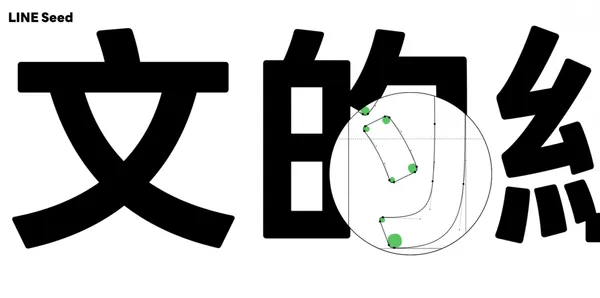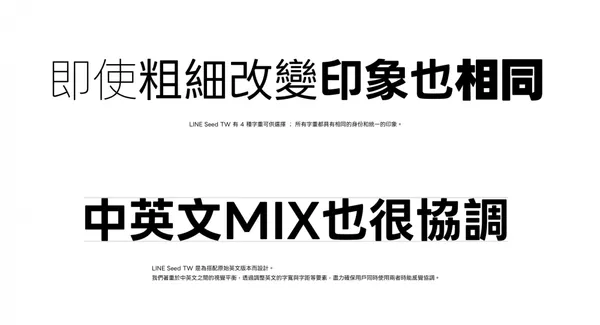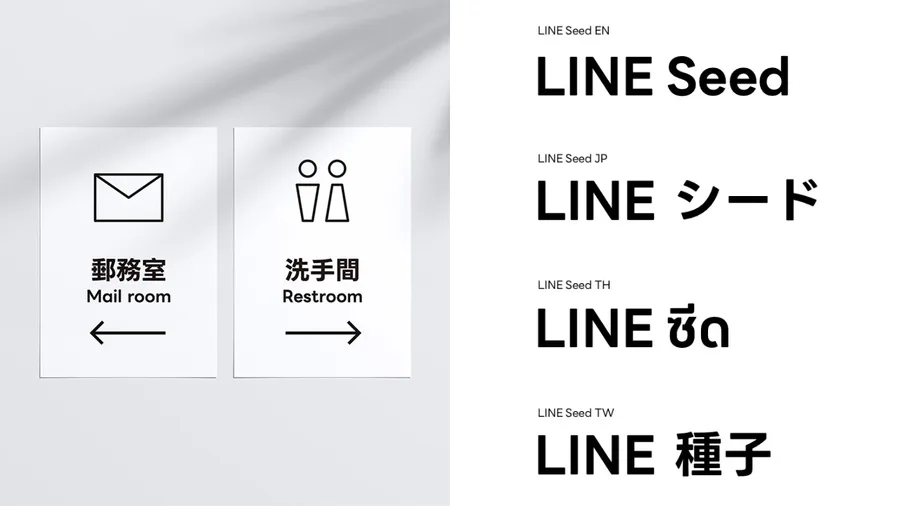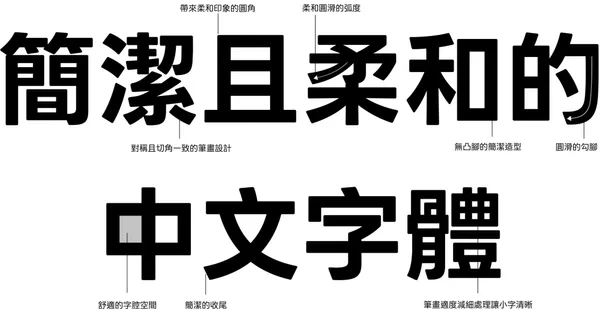
3 年磨出 14,038 字!LINE Seed 繁中版 4 款粗細一次收,可免費下載「商用也 0 元」
歷時近 3 年設計,LINE 首款自有字體「LINE Seed」,正式推出繁體中文版,共提供 4 種不同粗細的字重,可於 LINE Seed 官網免費下載,個人與商業用途均可使用。
LINE Seed 是一款強調簡約設計的無襯線字體,適用於數位、平面等各式使用場景。它保留了 LINE 品牌 Logo 的幾何造型,同時融入柔和的曲線,兼具理性與親和度。即使在中、英文字體並置時,視覺上也能和諧呈現。
攜手華康字型,LINE Seed 繁中字體設計亮點
LINE Seed 是由 LINE 所開發的企業字型,隨著品牌在全球提供服務,該字型也先後釋出了日文、英文、韓文、泰文等語言版本,如今,LINE 與華康字型(威鋒數位) 攜手合作,正式推出繁體中文版。
LINE Seed 繁體中文版共有 14,038 個字符,以日文版為基礎延伸開發,承襲英文版的圓角設計語言,並保留了 LINE Logo 的幾何造型。
在視覺上,則延續品牌識別風格,以「看起來舒服、讀起來親切,讓每一句話更有溫度」作為風格定義,精心調整每一個字符的筆畫與空間配置,在保持識別度的同時兼具應用彈性,無論是印刷、數位、多語言混合等情境,都具有高度的可讀性、辨識性、便利性,展現出理性與親和並存的設計理念。
LINE Seed 繁體中文版,設計過程遭遇哪些挑戰?
在製作過程中,為對應繁體中文的繁複筆畫與龐大字數,設計團隊投入大量時間進行筆劃定調與結構調整,確保可讀性與排版穩定性。
例如:在「北」字的設計上,團隊需在教育部標準字形、日文漢字寫法,以及 LINE 品牌想呈現的繁中風格之間反覆調整,並考量到最粗字重時筆劃是否會發生黏合,兼顧辨識度與排版的穩定。
為進一步強化細節品質與排版呈現,還需優化不同語言之間的一致性,例如:中英混排下的字距、標點對齊與高度調和等細節,最終推出 4 種不同粗細的字重,滿足標題、內文與細文字排版等多元需求。
最後,LINE 品牌官方也表示,之所以將旗下首個自有字體命名為「LINE Seed」,是期待該字體系統以「種子(Seed)」為寓意,逐漸發芽、結成果實,深植在 LINE 的服務之中,與使用者一同成長。
LINE Seed 繁體中文版